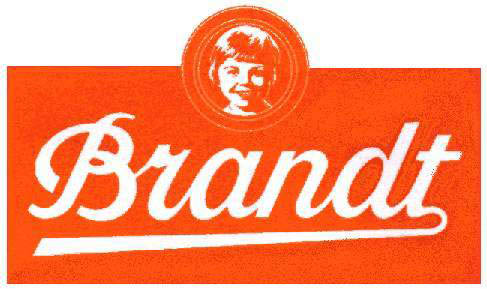
Neue Runde Typo-Quizz gefällig?
Ja, die Farbe ist original (vielleicht nicht der exakte RGB-Wert, den sie sonst nehmen, aber auf jeden Fall sehr nah dran), der Winkel auch.
OMG! Und ich dachte noch: Das ist doch eine Futura-Punze. Das macht einem ja richtig Angst. Eine Schrift an aus einer Ellipse erkennen. *kopfschüttel*
Die Wetten-dass-Wette sollte nicht lauten, 100 Schriften allein an einem a zu erkennen, sondern an einer Punze! :D
So, weiterraten …
Keine Panik, Ralf, ich habe da keine Schrift erkannt :oops:, ich hab einfach plötzlich das Bild vor Augen gehabt. Sowas wurde in meiner Kindheit und Jugend mit Dalli-Klick trainiert! Das Quiz hier ist ein einziges Dejavú...:shock:
DAs ist ja fast zu leicht: Lätta (das war ein blödes Wortspiel, ich geb's zu).
Betthupferl sollen ja auch leicht sein... :? Dubisdran!
Jau, das ist einfach und trocken. Aber vielleicht will ja mal jemand anderes...
So einfach ist das nicht. Ich dachte ja erst an Leica, aber das ist es nicht. Mmh. Oder hab ich Tomaten auf den Augen?